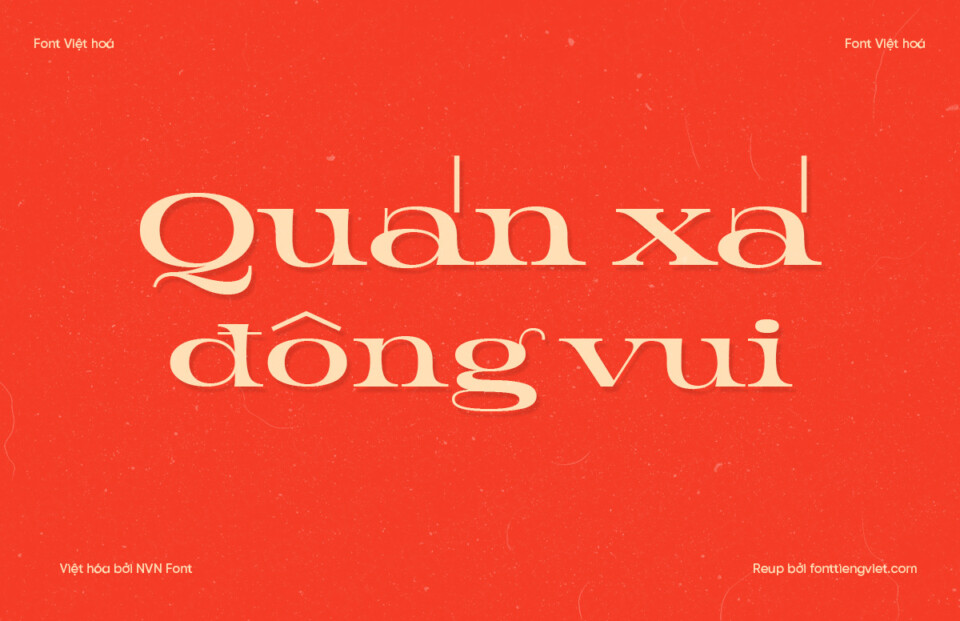
Font Việt hóa NVN Jeames
Giới thiệu về Font Việt hóa NVN Jeames trong thiết kế đồ họa
Trong thế giới sáng tạo, việc lựa chọn một bộ Font Miễn Phí chất lượng luôn là ưu tiên hàng đầu của các bạn học sinh và nhà thiết kế trẻ. Font Việt hóa NVN Jeames nổi lên như một hiện tượng nhờ sự kết hợp độc đáo giữa phong cách cổ điển phương Tây và tính ứng dụng hiện đại. Đây là bộ phông chữ được tinh chỉnh kỹ lưỡng để phù hợp hoàn toàn với hệ thống bảng mã tiếng Việt, giúp người dùng không còn lo lắng về lỗi nhảy chữ hay thiếu dấu khi soạn thảo nội dung. NVN Jeames mang trong mình hơi thở của những tấm biển quảng cáo thế kỷ 19 nhưng lại vô cùng tinh tế khi đặt vào các bối cảnh thiết kế đương đại.
Đặc điểm nổi bật giúp Font Việt hóa NVN Jeames chiếm trọn lòng tin
Cấu trúc chữ độc đáo và phá cách
Font Việt hóa NVN Jeames gây ấn tượng mạnh mẽ bởi các đường nét dày dặn, vững chãi kết hợp với những đường cong uyển chuyển ở các góc cạnh. Sự tương phản giữa các nét thẳng và nét bo tròn tạo nên một nhịp điệu thị giác thú vị. Điều này giúp bộ font không chỉ đơn thuần là công cụ truyền tải thông tin mà còn là một tác phẩm nghệ thuật độc lập. Đối với các bạn học sinh, bộ font này cực kỳ phù hợp để làm tiêu đề bài thuyết trình hoặc thiết kế bìa báo tường, giúp tác phẩm trở nên chuyên nghiệp và bắt mắt hơn hẳn so với các phông chữ hệ thống thông thường.
Khả năng tương thích và đa dạng ứng dụng
Không chỉ dừng lại ở vẻ bề ngoài, Font Việt hóa NVN Jeames còn ghi điểm bởi tính đa năng. Bạn có thể sử dụng nó cho nhiều mục đích khác nhau như thiết kế logo, poster phim, bao bì sản phẩm hay thậm chí là các ấn phẩm học đường. Bộ font này hoạt động mượt mà trên các phần mềm thiết kế phổ biến như Photoshop, Illustrator, Canva hay Microsoft Word. Đặc biệt, việc đã được Việt hóa 100% giúp các dấu thanh như huyền, sắc, hỏi, ngã, nặng được đặt đúng vị trí, tạo nên sự cân đối hoàn hảo cho toàn bộ đoạn văn bản.
Cách sử dụng Font Việt hóa NVN Jeames hiệu quả nhất
Kết hợp với các yếu tố màu sắc cổ điển
Để phát huy tối đa vẻ đẹp của Font Việt hóa NVN Jeames, người dùng nên kết hợp với các tông màu trầm hoặc màu nâu đất để tạo nên phong cách retro. Việc sử dụng độ tương phản cao giữa màu chữ và màu nền cũng giúp nội dung trở nên nổi bật và dễ đọc hơn từ khoảng cách xa. Hãy thử áp dụng các hiệu ứng đổ bóng nhẹ hoặc viền chữ để tạo chiều sâu, biến những dòng chữ đơn điệu thành một điểm nhấn đầy tính nghệ thuật trên trang thiết kế của bạn.
Lưu ý về kích thước và bố cục
Vì Font Việt hóa NVN Jeames thuộc dòng font có cá tính mạnh, bạn nên ưu tiên sử dụng nó cho các tiêu đề chính hoặc các đoạn văn ngắn quan trọng. Tránh sử dụng bộ font này cho các văn bản dài (body text) vì các chi tiết phức tạp có thể gây mỏi mắt cho người đọc. Một bố cục thoáng đãng với khoảng cách giữa các chữ cái được căn chỉnh hợp lý sẽ giúp bộ phông chữ tỏa sáng rực rỡ nhất trong mọi không gian trình bày.